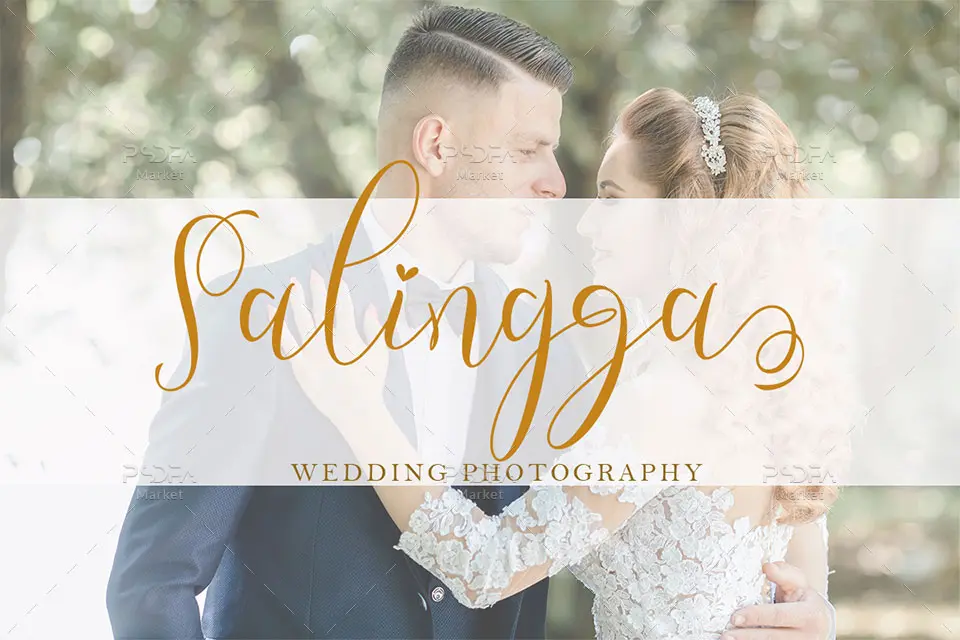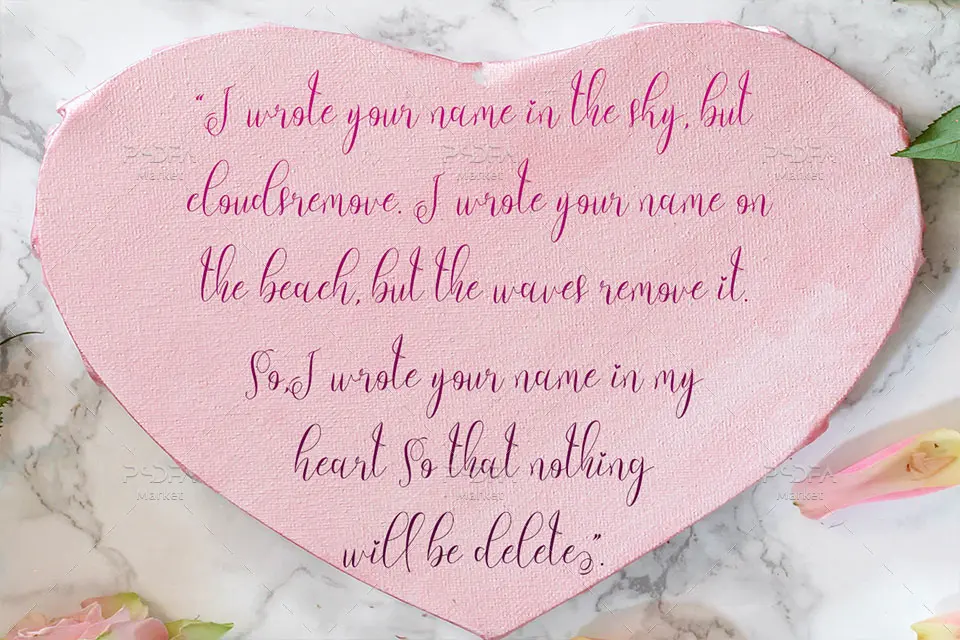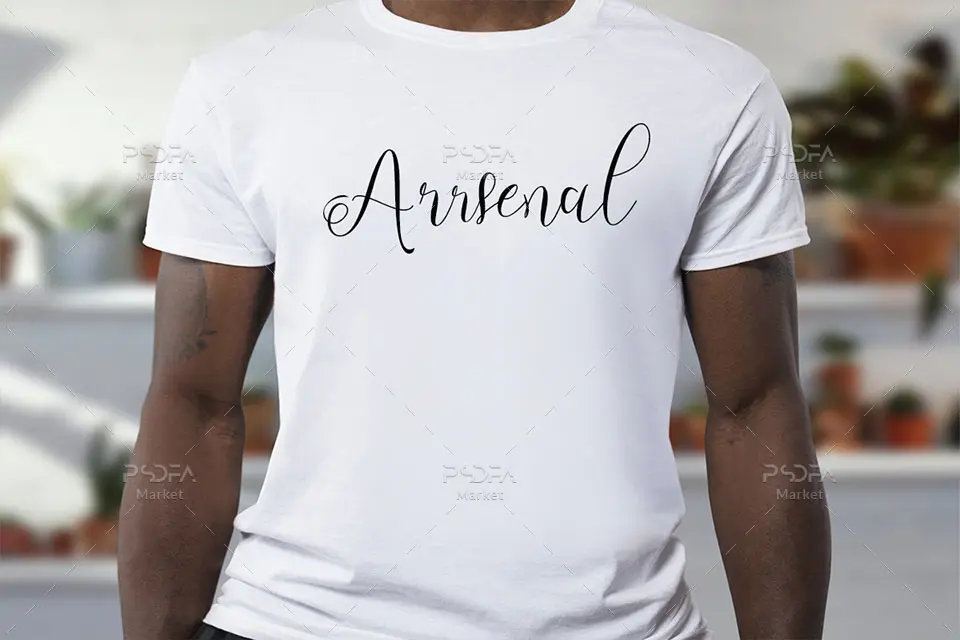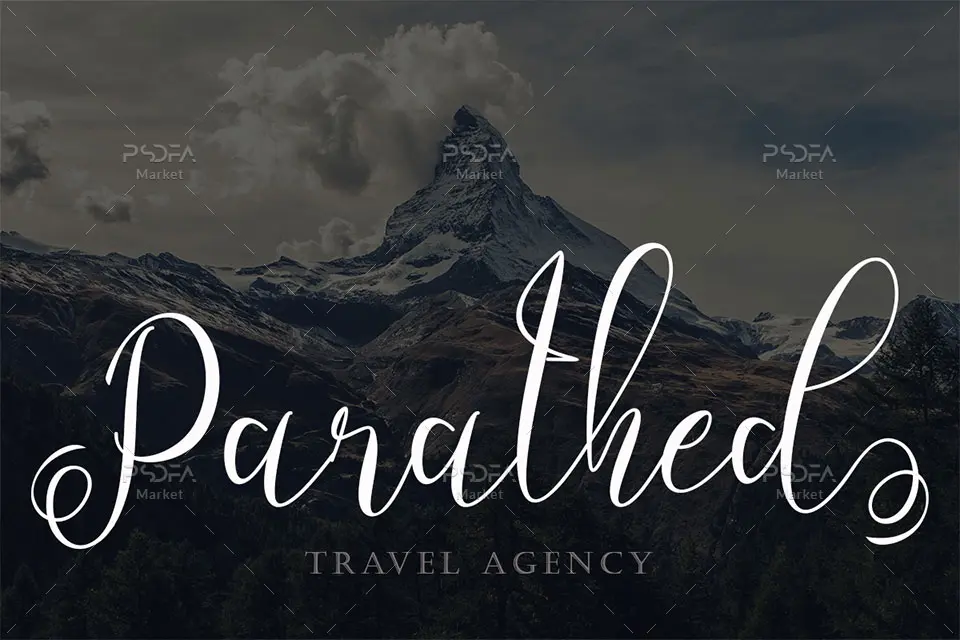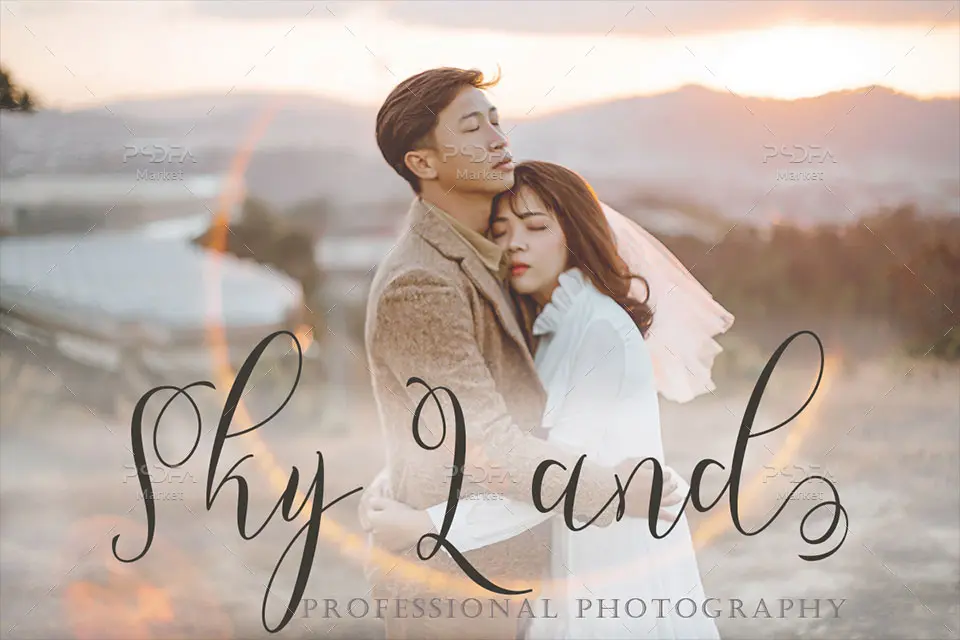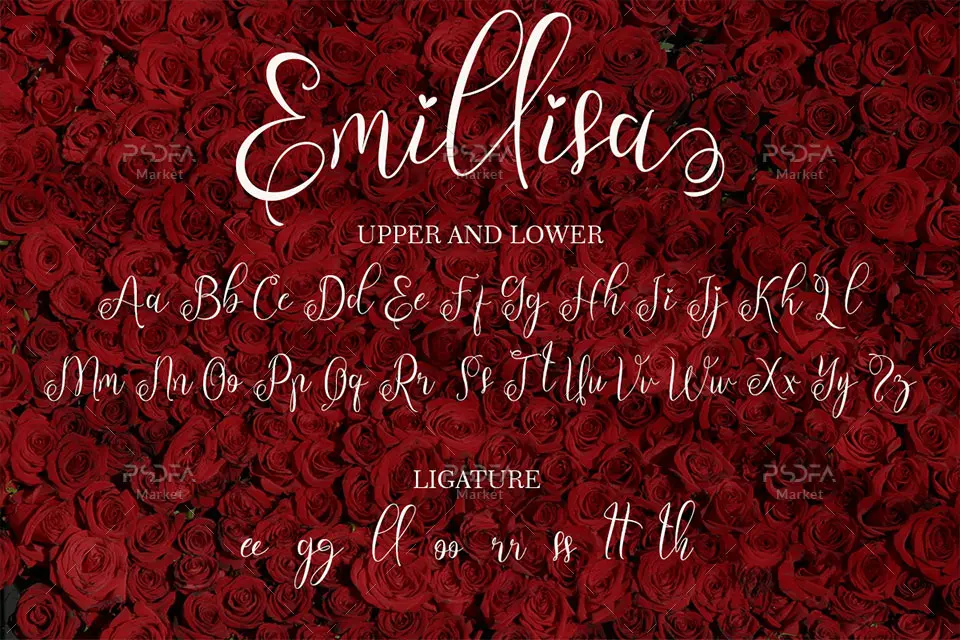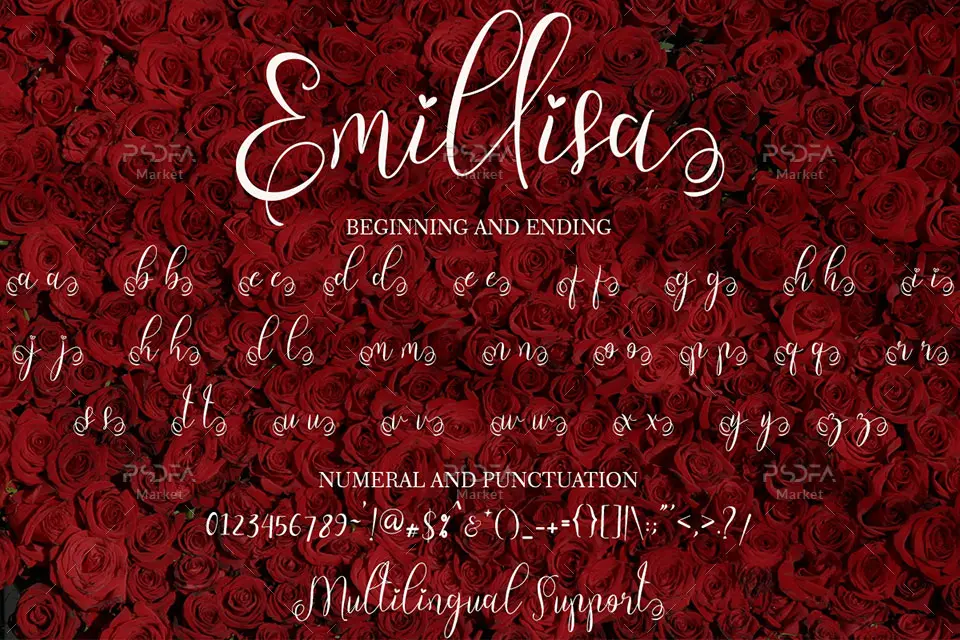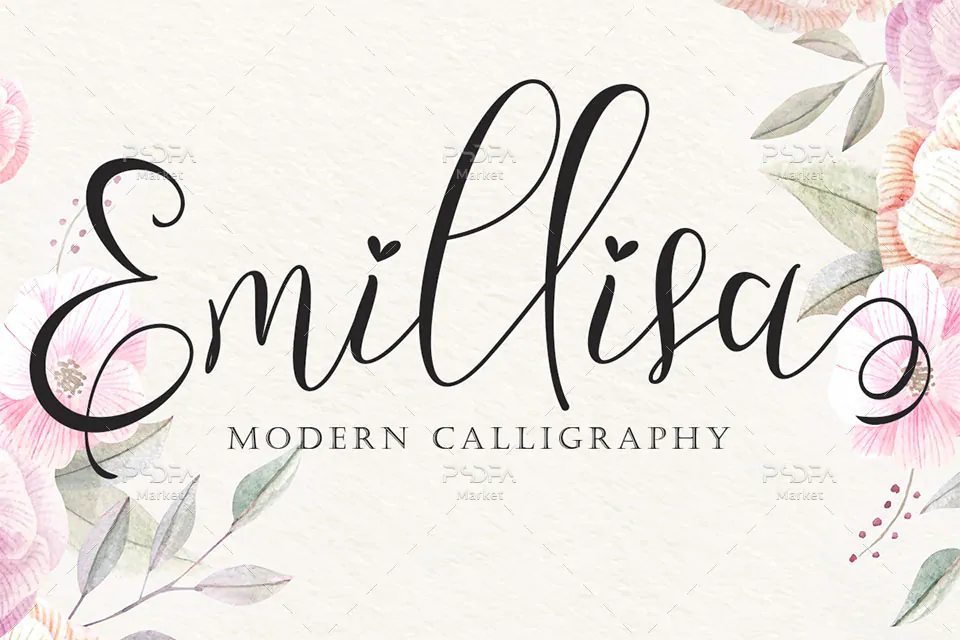
فونت رمانتیک و عاشقانه Emillisa یک قلم فوقالعاده زیبا و جالب است که به صورت دستنویس طراحی و ایجاد شده است که شما میتوانید از آن در طرح و پروژههای گرافیکی خود به خصوص طراحی انواع پوستر استفاده کنید. این فونت زیبا در قالب 2 فایل otf, ttf بر روی سایت قرار گرفته است که با نصب یکی از این دو فرمت در پوشه فونتهای سیستم، میتوانید از آن در تمام نرمافزارهای گرافیکی و ویرایشگر متن از جمله فتوشاپ، پریمیر، افتر افکت، مجموعه نرمافزار آفیس و … استفاده کنید.
ویژگیهای قلم و فونت Emillisa
فونت Emillisa در وزن معمولی (Regular) طراحی شده است که شما میتوانید از آن در طراحی انواع کارت تبریک، کارت پستال، کارت ویزیت، طراحی انواع بنر یا پوستر، تراکت، تقویم و دیگر طرحهای گرافیکی استفاده کنید.
- کیفیت بالای قلم
- نام فونت: Emillisa
- وزن: (Regular)